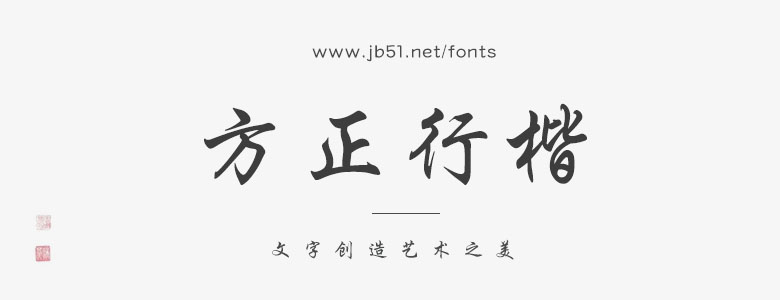
方正行楷由書法家任政創(chuàng)作。這款字體介于楷書與行書之間,偏重于楷書書寫筆法,既比楷書行筆自由,又比行書規(guī)整的一種書寫字體。其行筆流暢自然,筆畫雄渾有力,是一款易識(shí)性較高的書寫字體。方正行楷家族有5個(gè)字重,風(fēng)格剛勁舒展,適用于文化類的宣傳設(shè)計(jì),以及商業(yè)類品牌的廣告和產(chǎn)品包裝設(shè)計(jì)。